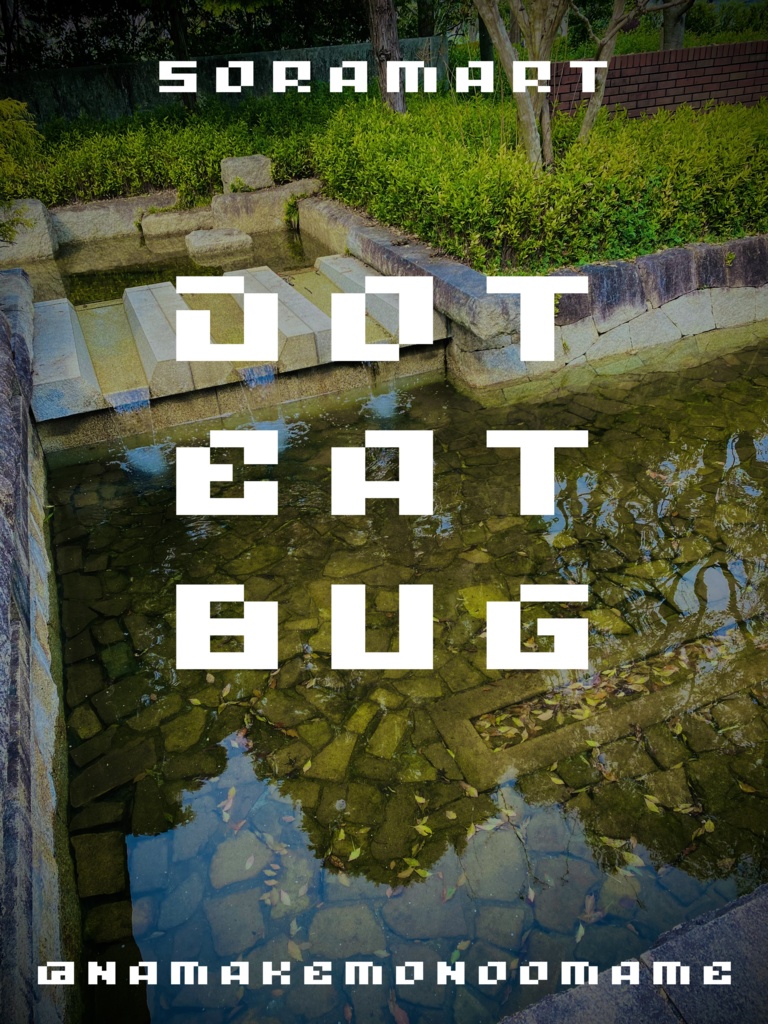
そらマートフォントデータ”Dot Eat Bug”Digital2,500 JPY放入購物車Buy a GiftAbout Gift”バグ”をイメージしたドット調フォント "Dot Eat Bug" です。 「TrueTypeフォントファイル」という形式です。 ダウンロードした後、Zipファイル内のデータをインストールしてお使いください。 このフォントは商用利用可となっております。 お客様の制作・創作活動のお役に立てれば幸いです。 ※使用上の注意事項などは、添付のReadmeをお読みください。そらマートVisit FANBOX!Fontsフォントデータ”RANMMA Drive”そらマート0 JPYFontsフォントデータ”Dandy Laser Max”そらマート2,500 JPYFontsフォントデータ”Dandy Laser”そらマート2,500 JPYFontsフォントデータ”Bubblegum Beat”そらマート2,500 JPYFontsフォントデータ”Caltrop Serif LLL”そらマート2,500 JPYFontsフォントデータ”Caltrop Serif LL”そらマート2,500 JPYFontsフォントデータ”Caltrop Serif”そらマート2,500 JPYFontsフォントデータ”Tonik Crate Super Long”そらマート2,500 JPYFontsフォントデータ”Dot Eat Bug Acid”そらマート2,500 JPYFontsフォントデータ”Dot Eat Bug Mild”そらマート2,500 JPYFontsフォントデータ”Solid Voltage Strike”そらマート2,500 JPYFontsフォントデータ”Solid Voltage”そらマート2,500 JPYFontsフォントデータ”Henge Edge Rock”そらマート2,500 JPYFontsフォントデータ”Henge Edge Tall”そらマート0 JPYFontsフォントデータ”Henge Edge”そらマート0 JPYFontsフォントデータ”Chisel Stroke Wide”そらマート2,500 JPYFontsフォントデータ”Chisel Stroke”そらマート2,500 JPYFontsフォントデータ”Crushed Can Serif Empty”そらマート2,500 JPYFontsフォントデータ”Crushed Can Serif Wide”そらマート2,500 JPYFontsフォントデータ”Crushed Can Serif”そらマート2,500 JPY查看更多